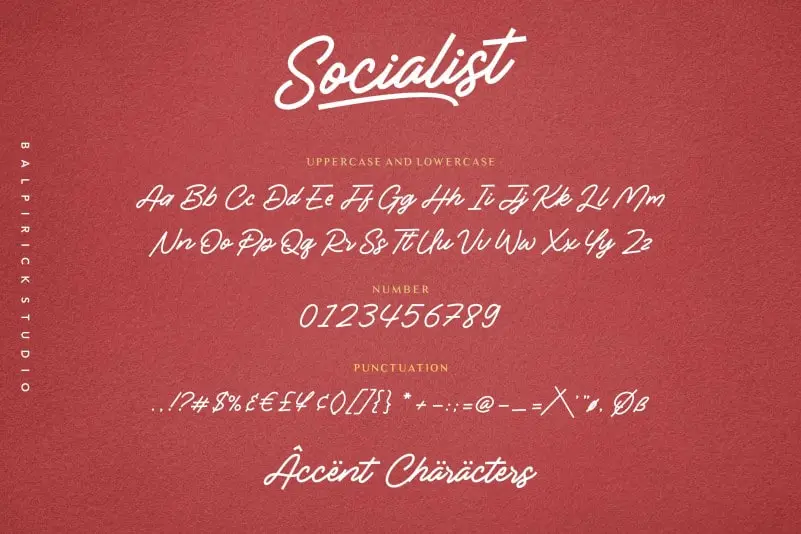
A Socialist Monoline Font é perfeitamente adaptada para diversas aplicações na identidade visual, especialmente para projetos que valorizam simplicidade e clareza. Suas linhas retas e fortes fazem dela uma escolha inteligente para aplicar em embalagens de produtos ou etiquetas, garantindo um design atraente mesmo sob pequenas dimensões. Com seus traços nítidos e sólidos, é perfeita para criações que exigem presença na cena do design, como logotipos, cartas de convite ou materiais promocionais, proporcionando uma estética moderna e moderna. Além disso, a sua simplicidade faz com que ela seja ideal para ambientes digitais, desde postagens em redes sociais até sites e blogs. Seja para criar um apelo forte nos materiais de imprensa ou para decorar cartões de casamento, esta fonte manterá seu design claro e assertivo.